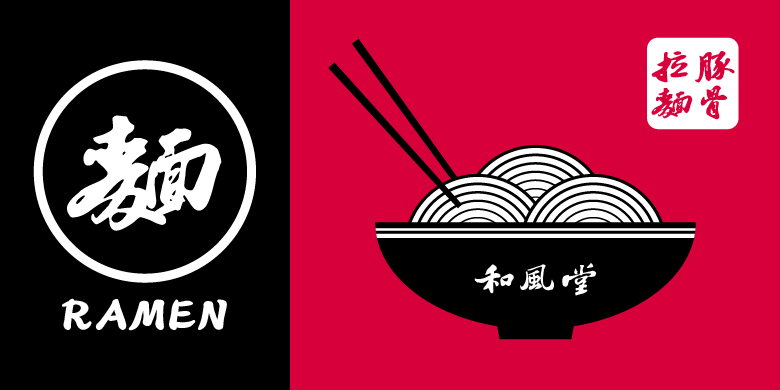
字體名稱: 書體坊蘇軾行書
書體坊蘇軾行書
書體坊蘇軾行書,以蘇軾流傳后世的書法作品為字源,以《洞庭春色賦》《中山松醪賦》《赤壁賦》《歸去來兮辭》《寒食貼上》《西山詩帖》等作品字形為基本,集字制作而成。字體在結(jié)字上,突出蘇軾書法的主要特征,結(jié)字扁平,撇捺筆畫舒展,橫輕豎重,輕重錯(cuò)落;在用墨上,豐腴肥美,字字豐潤,嫵媚娟秀,樸拙厚重,平和中正。字體風(fēng)格整體統(tǒng)一,體現(xiàn)了蘇軾書法的主要風(fēng)貌。